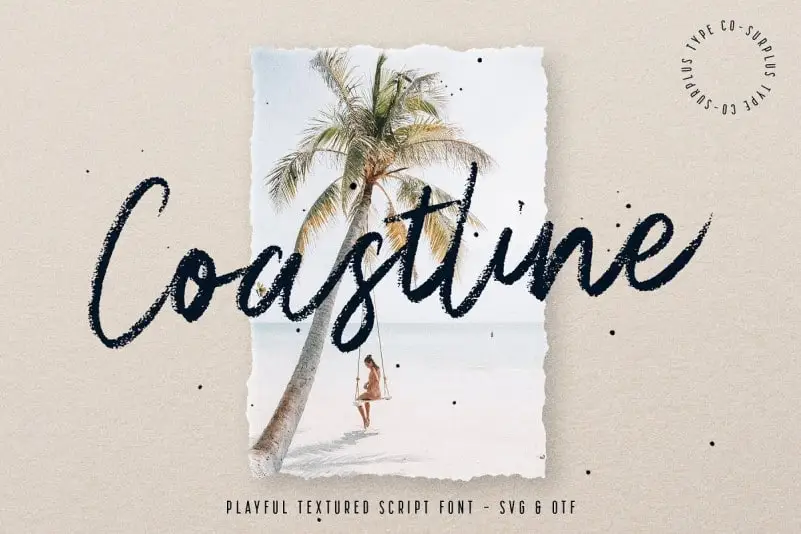
A fonte “Coastline Brush Font” é uma elegante caligrafia suave com textura, desenvolvida por Surplus Type Co. Esta fonte combina elementos regulares e alternativos de script bold, ideal para diversas áreas do design gráfico. Suas linhas leves e delicadas, combinadas com um toque moderno, permitem criar designs que vão desde agradáveis citações até publicações e anúncios. A fonte também é ótima para incorporar em objetos físicos como roupas, posters e itens de decoração da casa. Seja você designer ou criador de conteúdo digital, a “Coastline Brush Font” oferece uma opção versátil para seus projetos, garantindo que sua arte seja não só atraente, mas também única. Com sua textura única e design limpo, esta fonte é um verdadeiro alívio para os olhos, tornando-a perfeita para qualquer projeto em que você queira deixar sua marca de maneira elegante e sofisticada.